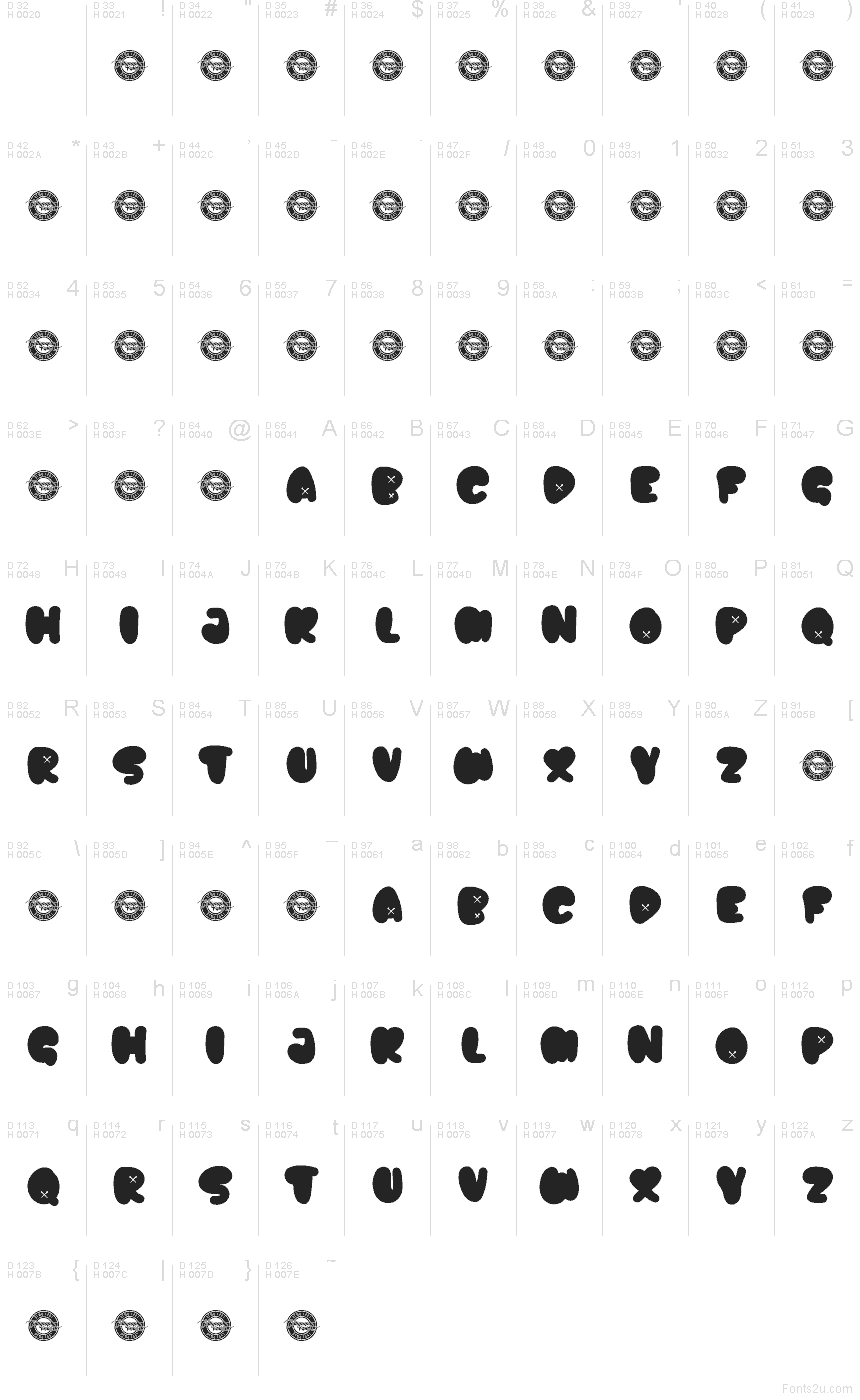
Smoke Bomb Demo
Smoke Bomb от CalligraphyFonts.net - это бесплатный мультяшный шрифт, состоящий из раздутых, дымчатых силуэтов, отчего каждая буква кажется объемной и слегка надутой. Округлые черные формы создают мягкий, «пузырьковый» ритм, поэтому дизайн скорее напоминает клубящийся рисованный дым, чем обычный декоративный шрифт.
Эта объемная текстура отлично смотрится в коротких заголовках на обложках комиксов, приглашениях на детские праздники, хэллоуинской графике, заголовках игр и плакатах. Smoke Bomb также идеален для наклеек и постов в соцсетях, где эти облакообразные формы позволяют быстро оформить слово без использования дополнительных иллюстраций.